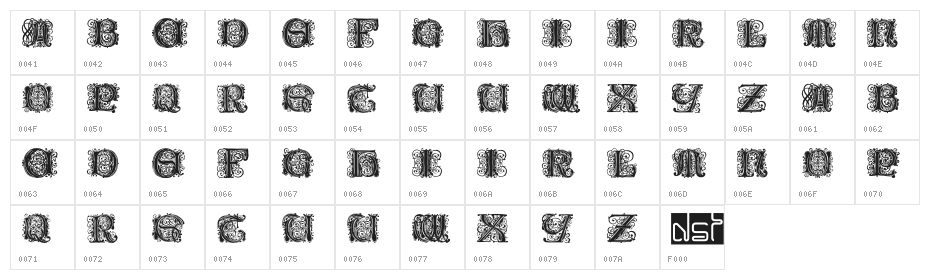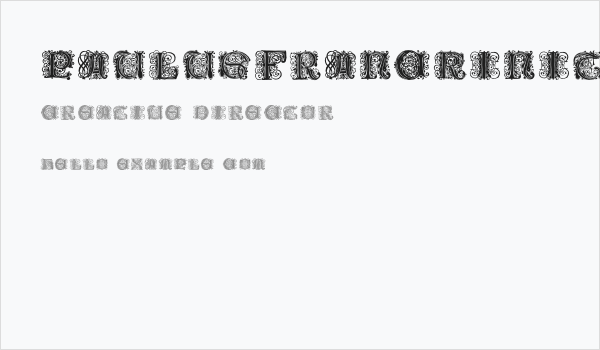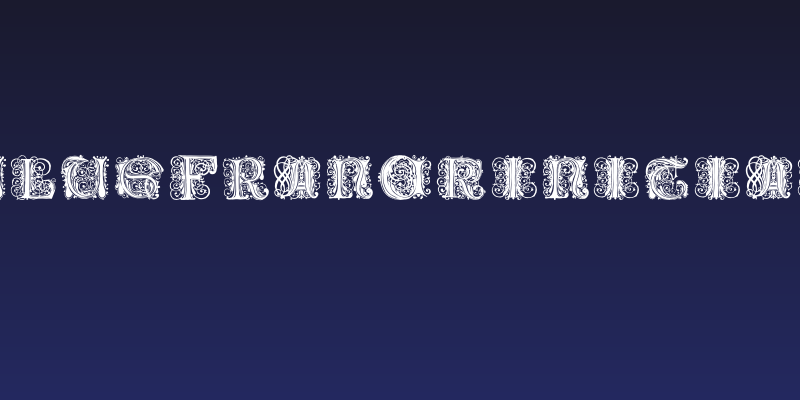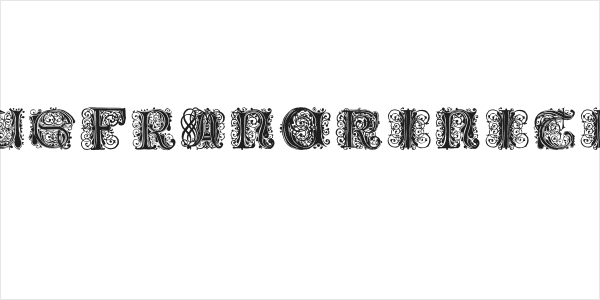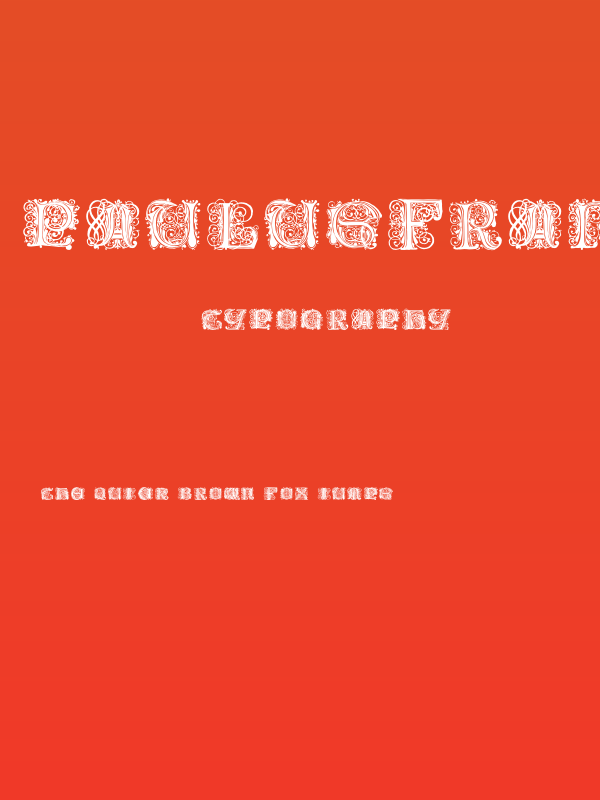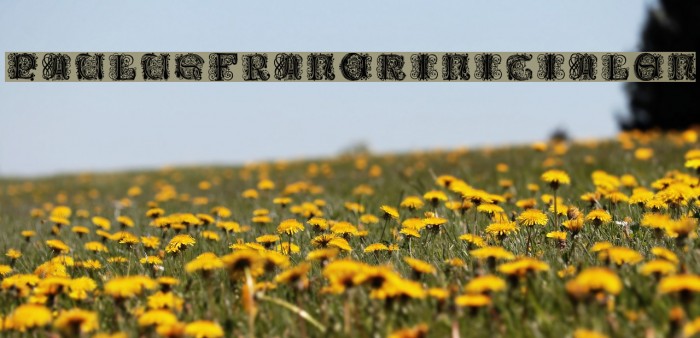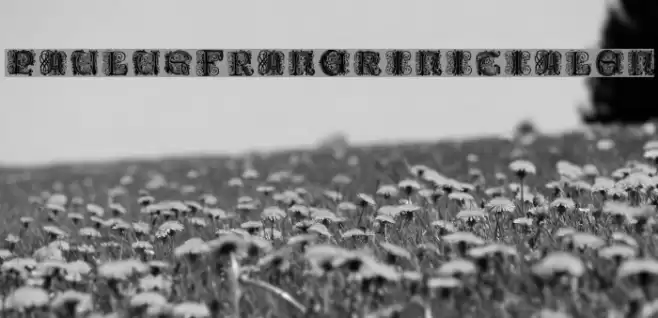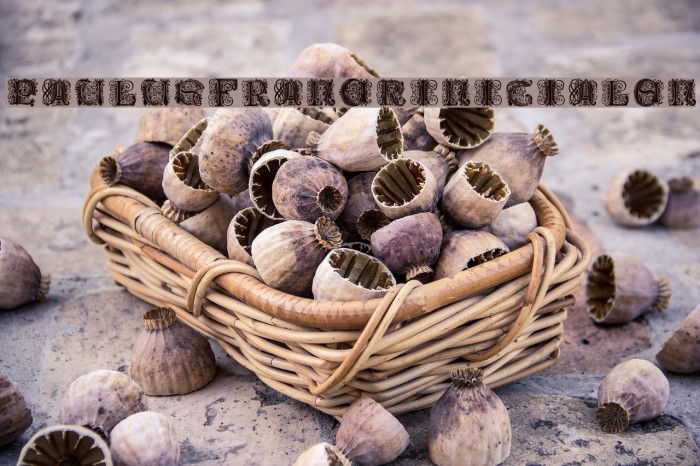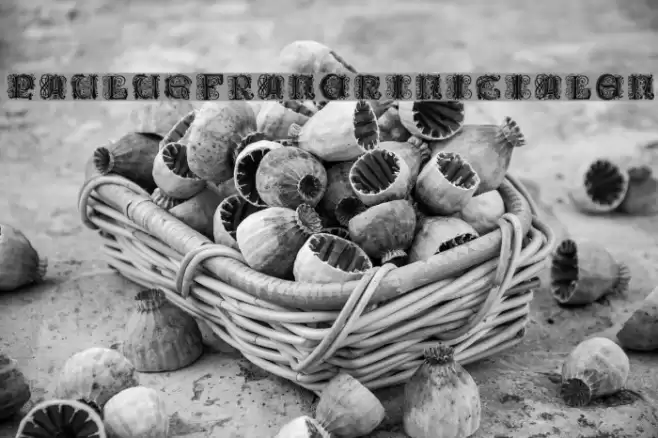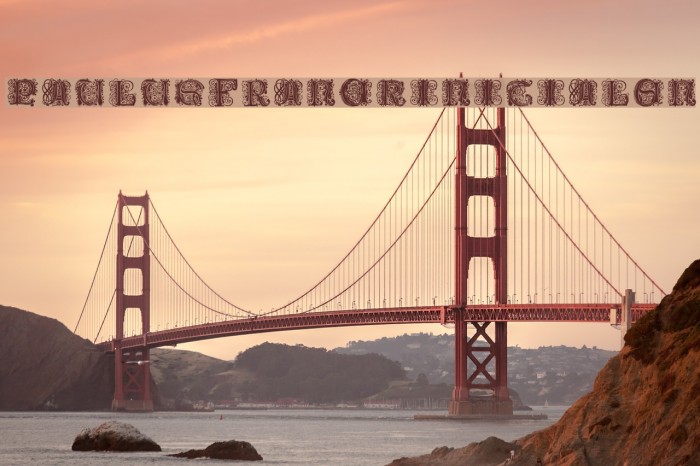
PaulusFranckInitialen Font
✎ Curly
| 用途 | Logos, Headlines, Decorative purposes |
| おすすめプロジェクト | Ideal for wedding invitations, historical-themed projects, luxury branding, and decorative book covers. |